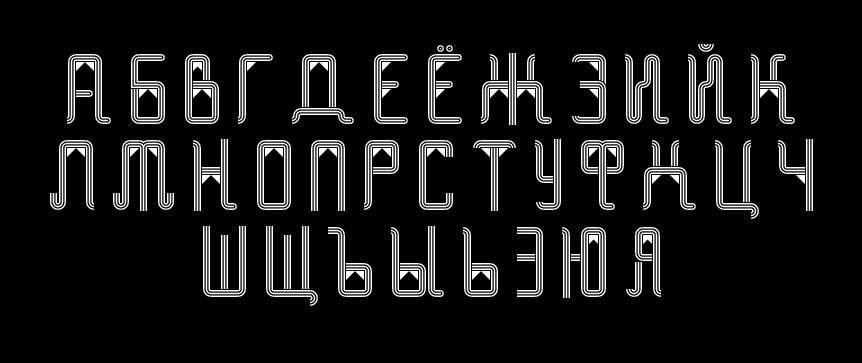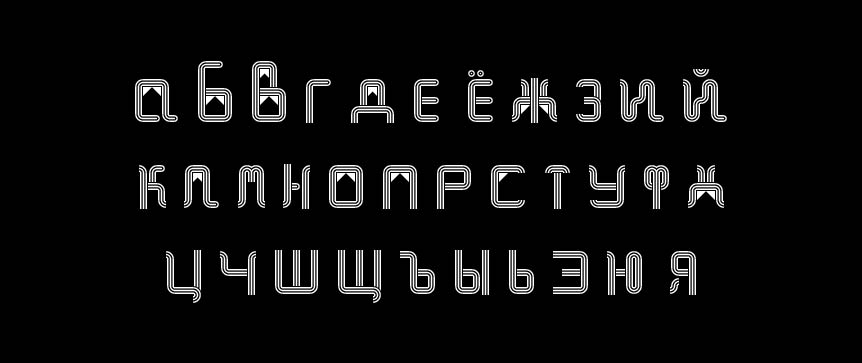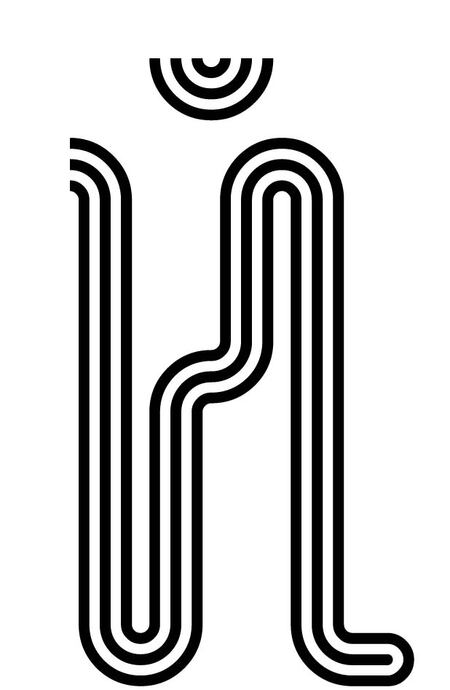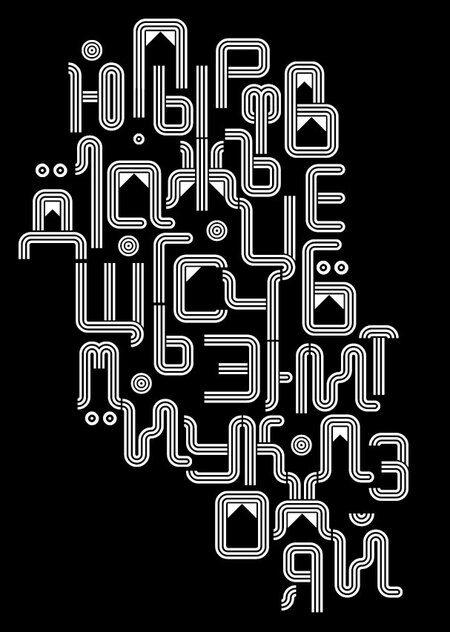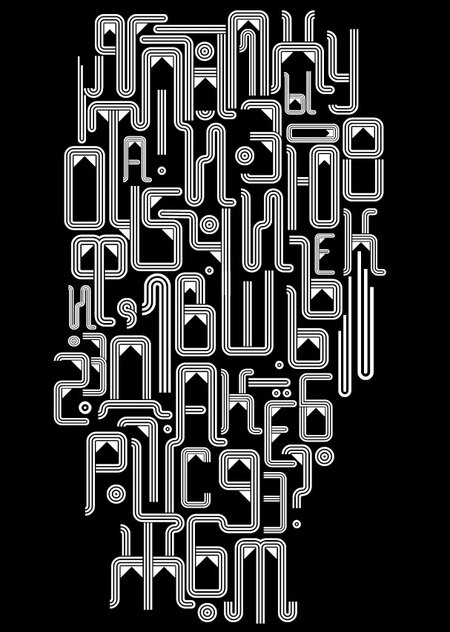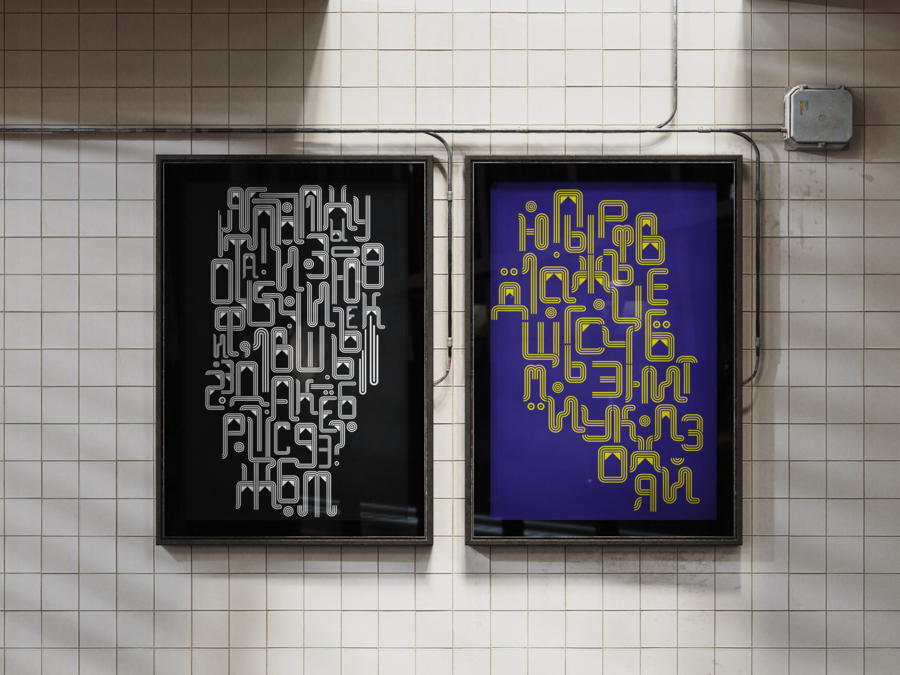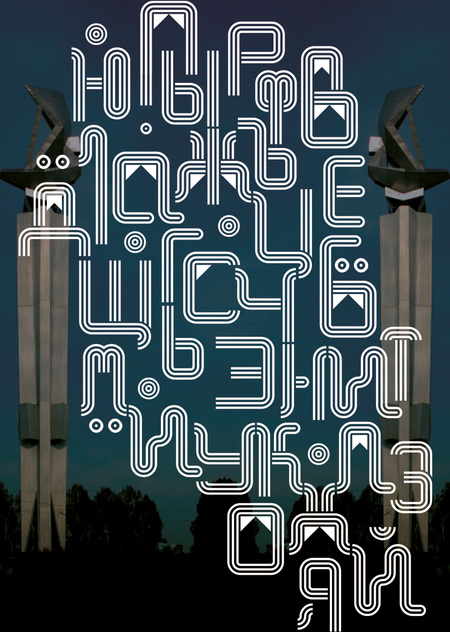
Шрифтовая система Togliatti Contours Typeface вдохновлённым городом Тольятти.
В основу проекта заложен принцип отражения урбанистической структуры города через типографику. Тольятти — уникальный пример советского модернизма, где город разделен на три автономных района, соединенных между собой сетью прямых магистралей и кольцевых развязок. Шрифт является прямой визуальной метафорой этих топологических особенностей.В крупном размере шрифт читается как скульптурный объект, в мелком наборе создает оптический эффект дорожной сети, сохраняя свою жесткую, текстурирующую способность.Шрифт рекомендуется использовать в монохроме
Шрифтовые компазиции